ฟอนต์มีผล! เลือกฟอนต์อย่างไรให้แบรนด์ดูโปร น่าเชื่อถือ
การเลือกใช้ฟอนต์มีผลอย่างยิ่งต่อการรับรู้ของลูกค้า การเลือกฟอนต์ที่เหมาะสมสามารถช่วยให้แบรนด์ดูเป็นมืออาชีพและสร้างความน่าเชื่อถือได้อย่างมีนัยสำคัญ ในทางกลับกัน การเลือกที่ไม่ถูกต้องอาจทำให้ภาพลักษณ์ของแบรนด์ดูไม่เป็นมืออาชีพและขาดความน่าเชื่อถือได้ ฟอนต์ไม่ใช่เพียงองค์ประกอบด้านการออกแบบ แต่เป็นเครื่องมือสื่อสารที่ทรงพลังในการถ่ายทอดบุคลิกและคุณค่าของแบรนด์ไปยังกลุ่มเป้าหมาย
ภาพรวมของการเลือกฟอนต์เพื่อสร้างแบรนด์
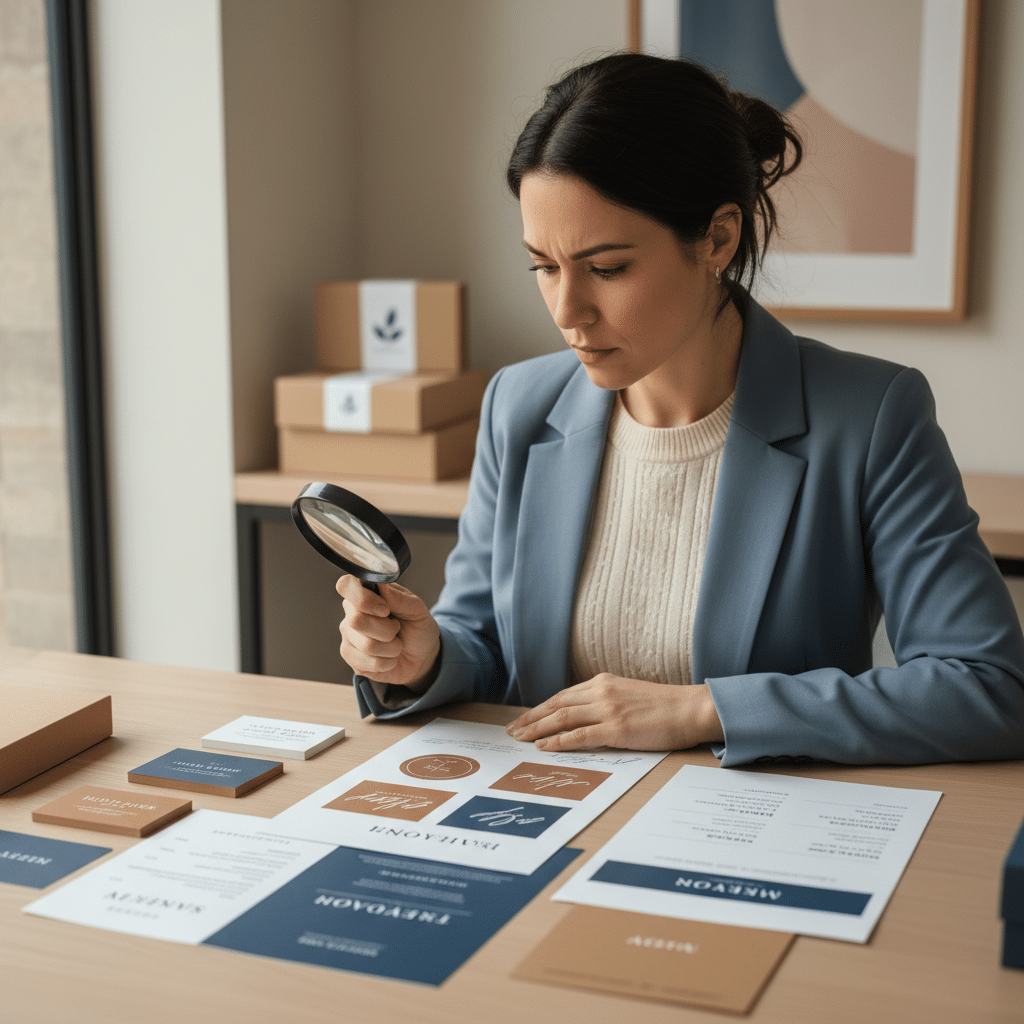
- ฟอนต์คือ ‘เสียง’ ของแบรนด์: รูปแบบของตัวอักษรสามารถสื่อสารอารมณ์และบุคลิกของแบรนด์ได้โดยไม่ต้องใช้คำพูด ตั้งแต่ความหรูหรา คลาสสิก ไปจนถึงความทันสมัยและเป็นกันเอง
- ความสอดคล้องคือกุญแจสำคัญ: การเลือกฟอนต์ต้องสอดคล้องกับบุคลิกของแบรนด์ กลุ่มเป้าหมาย และสารที่ต้องการจะสื่อ เพื่อสร้างภาพจำที่ชัดเจนและแข็งแกร่ง
- จิตวิทยาของฟอนต์: ฟอนต์แต่ละประเภท เช่น Serif, Sans Serif, หรือ Script มีผลทางจิตวิทยาต่อผู้รับสารแตกต่างกัน การทำความเข้าใจในเรื่องนี้ช่วยให้สามารถเลือกฟอนต์ที่กระตุ้นความรู้สึกที่ต้องการได้อย่างแม่นยำ
- ความเรียบง่ายสร้างการจดจำ: การจำกัดการใช้ฟอนต์เพียง 1-2 รูปแบบในงานออกแบบหนึ่งชิ้น จะช่วยสร้างความเป็นระเบียบ อ่านง่าย และทำให้ผู้บริโภคจดจำเอกลักษณ์ของแบรนด์ได้ดียิ่งขึ้น
บทนำ: ทำไมฟอนต์จึงสำคัญต่อภาพลักษณ์ธุรกิจ
ในโลกธุรกิจที่มีการแข่งขันสูง การสร้างความแตกต่างและภาพลักษณ์ที่น่าจดจำเป็นสิ่งสำคัญอย่างยิ่ง หนึ่งในองค์ประกอบที่มักถูกมองข้ามแต่มีอิทธิพลสูงคือ “ฟอนต์” หรือ “ไทโปกราฟี” (Typography) ฟอนต์ไม่ใช่แค่ตัวอักษรที่ใช้นำเสนอข้อมูล แต่เป็นองค์ประกอบสำคัญของอัตลักษณ์ทางภาพ (Visual Identity) ที่ทำหน้าที่เป็น “เสียง” หรือ “น้ำเสียง” ของแบรนด์ในการสื่อสารกับลูกค้า
สำหรับผู้ประกอบการ SME นักการตลาด และนักออกแบบ การทำความเข้าใจว่า ฟอนต์มีผล! เลือกฟอนต์อย่างไรให้แบรนด์ดูโปร น่าเชื่อถือ จึงเป็นทักษะที่จำเป็นอย่างยิ่ง การเลือกฟอนต์ที่เหมาะสมสามารถยกระดับแบรนด์ให้ดูเป็นมืออาชีพ สร้างความไว้วางใจ และเชื่อมโยงกับกลุ่มเป้าหมายทางอารมณ์ได้ ในขณะที่การเลือกฟอนต์ที่ไม่สอดคล้องกันอาจส่งผลเสียต่อภาพลักษณ์ ทำให้แบรนด์ดูไม่น่าเชื่อถือ หรือสื่อสารบุคลิกของแบรนด์ผิดเพี้ยนไป บทความนี้จะเจาะลึกถึงหลักการและจิตวิทยาเบื้องหลังการเลือกฟอนต์ เพื่อเป็นแนวทางในการสร้างแบรนด์ให้แข็งแกร่งและประสบความสำเร็จ
หลักการพื้นฐานในการเลือกฟอนต์ให้เหมาะสมกับแบรนด์
ก่อนที่จะตัดสินใจเลือกฟอนต์ใดฟอนต์หนึ่ง การวางรากฐานที่มั่นคงด้วยหลักการพื้นฐานจะช่วยให้กระบวนการตัดสินใจเป็นไปอย่างมีเหตุผลและสอดคล้องกับเป้าหมายของแบรนด์มากที่สุด
กำหนดบุคลิกแบรนด์และกลุ่มเป้าหมาย
ขั้นตอนแรกและสำคัญที่สุดคือการทำความเข้าใจตัวตนของแบรนด์อย่างลึกซึ้ง ต้องตอบคำถามให้ได้ว่า แบรนด์ต้องการสื่อสารบุคลิกแบบใด? เป็นแบรนด์ที่เน้นความหรูหรา สง่างาม? หรือเป็นแบรนด์ที่ทันสมัย เข้าถึงง่าย และเป็นมิตร? หรืออาจจะเป็นแบรนด์ที่ดูมั่นคง แข็งแกร่ง และน่าเชื่อถือ? เมื่อกำหนดบุคลิกของแบรนด์ได้แล้ว ให้นำไปวิเคราะห์ร่วมกับข้อมูลของกลุ่มเป้าหมาย เพื่อเลือกรูปแบบฟอนต์ที่สามารถสื่อสารและสร้างความเชื่อมโยงกับพวกเขาได้อย่างมีประสิทธิภาพสูงสุด ตัวอย่างเช่น แบรนด์สินค้าสำหรับเด็กอาจเลือกใช้ฟอนต์ที่ดูสนุกสนานและเป็นกันเอง ในขณะที่สถาบันการเงินจะเลือกใช้ฟอนต์ที่ดูสุขุมและเป็นทางการเพื่อสร้างความน่าเชื่อถือ
ทดสอบการอ่านง่ายและความชัดเจน
ฟอนต์ที่สวยงามแต่ขาดความชัดเจนอาจส่งผลเสียมากกว่าผลดี หลักการสำคัญคือความสามารถในการอ่านง่าย (Readability) และความชัดเจนของตัวอักษรแต่ละตัว (Legibility) ต้องทดสอบฟอนต์ในขนาดที่แตกต่างกัน ตั้งแต่ขนาดใหญ่สำหรับพาดหัว ไปจนถึงขนาดเล็กสำหรับเนื้อหารายละเอียด และต้องทดสอบการแสดงผลบนแพลตฟอร์มที่หลากหลาย ทั้งบนหน้าจอคอมพิวเตอร์ แท็บเล็ต โทรศัพท์มือถือ และบนสื่อสิ่งพิมพ์ เพื่อให้แน่ใจว่าข้อความทั้งหมดจะยังคงชัดเจนและสื่อสารได้อย่างครบถ้วนในทุกสถานการณ์
จำกัดจำนวนฟอนต์เพื่อความสอดคล้อง
หลักการ “น้อยแต่มาก” ยังคงใช้ได้ดีกับการออกแบบไทโปกราฟี การใช้ฟอนต์หลากหลายรูปแบบมากเกินไปในงานออกแบบชิ้นเดียวจะสร้างความสับสนและดูไม่เป็นมืออาชีพ โดยทั่วไปแล้ว ควรจำกัดจำนวนฟอนต์ที่ใช้ไม่เกิน 2-3 รูปแบบ อาจเลือกใช้ฟอนต์หนึ่งสำหรับหัวข้อหลัก (Heading) และอีกฟอนต์หนึ่งสำหรับเนื้อหา (Body Text) การจับคู่ฟอนต์ที่แตกต่างกันอย่างมีชั้นเชิง เช่น การใช้ฟอนต์แบบ Sans Serif ที่ทันสมัยคู่กับฟอนต์ Serif ที่คลาสสิก สามารถสร้างคอนทราสต์ที่น่าสนใจและสมดุลได้ การใช้ฟอนต์ตระกูลเดียวกัน (Font Family) ที่มีน้ำหนักต่างกัน (เช่น Light, Regular, Bold) ก็เป็นอีกวิธีที่ช่วยสร้างลำดับชั้นของข้อมูลโดยยังคงความสอดคล้องของงานออกแบบไว้ได้
ตรวจสอบลิขสิทธิ์และการรองรับภาษา
ประเด็นทางเทคนิคและกฎหมายเป็นสิ่งที่ไม่ควรมองข้าม ต้องตรวจสอบให้แน่ใจว่าฟอนต์ที่เลือกใช้นั้นมีลิขสิทธิ์ที่ถูกต้องสำหรับการใช้งานในเชิงพาณิชย์ ฟอนต์ฟรีบางตัวอาจจำกัดการใช้งานเฉพาะส่วนบุคคลเท่านั้น สำหรับแบรนด์ในประเทศไทย การตรวจสอบว่าฟอนต์นั้นรองรับภาษาไทยอย่างสมบูรณ์เป็นสิ่งสำคัญอย่างยิ่ง ซึ่งรวมถึงการแสดงผลสระและวรรณยุกต์ที่ถูกต้องในทุกอุปกรณ์และระบบปฏิบัติการ เพื่อหลีกเลี่ยงปัญหาตัวอักษรผิดเพี้ยนหรือ “ฟอนต์ลอย” ที่อาจทำลายความเป็นมืออาชีพของแบรนด์ได้
เจาะลึกจิตวิทยาของฟอนต์: เลือกอย่างไรให้สื่อสารตรงใจ
ฟอนต์แต่ละรูปแบบมีพลังในการกระตุ้นความรู้สึกและการรับรู้ที่แตกต่างกัน การทำความเข้าใจจิตวิทยาเบื้องหลังฟอนต์ประเภทต่างๆ จะช่วยให้แบรนด์สามารถเลือกเครื่องมือสื่อสารที่ทรงพลังนี้ได้อย่างแม่นยำและตรงจุด
ฟอนต์ Serif สร้างความรู้สึกน่าเชื่อถือและเป็นทางการ ในขณะที่ Sans Serif ให้ภาพลักษณ์ที่ทันสมัยและเข้าถึงง่าย การเลือกที่ถูกต้องสามารถกำหนดการรับรู้ของลูกค้าที่มีต่อแบรนด์ได้ตั้งแต่แรกเห็น
ตารางด้านล่างนี้เปรียบเทียบประเภทฟอนต์ยอดนิยม ลักษณะเด่น และอุตสาหกรรมที่เหมาะสม เพื่อเป็นแนวทางในการเลือกใช้ให้สอดคล้องกับบุคลิกของแบรนด์
| ประเภทฟอนต์ | ลักษณะเด่น | เหมาะกับแบรนด์/อุตสาหกรรม | ตัวอย่างการสื่อสาร |